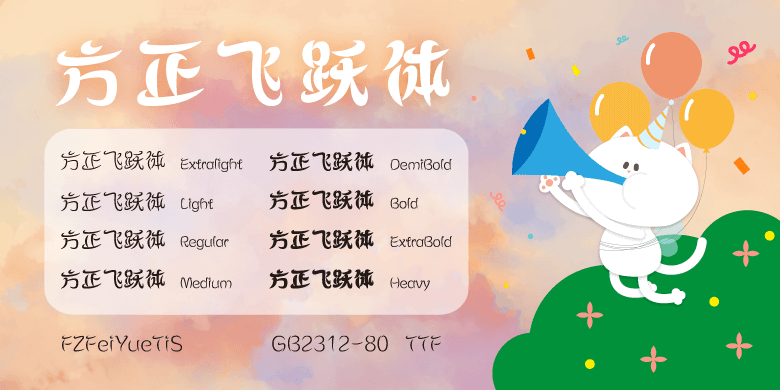
方正飞跃体-简繁-ExtraLight
方正飞跃体:一看这名字感受到活力和跳跃的感觉,设计灵感来源于郭老师在看运动会跨栏赛跑时,发现该名运动员的跑鞋上的标志,立即抓了这条大鱼(灵感)。飞跃体的特点是没有直线,全是弧线组成,横划都向右上角斜上,头部有一个弯钩,所有撇,捺,点都用弧线形表达,因此增强飞跃体的感觉,名副其实,飞跃体在设计上突破传统束缚,并带来创新悦目的感受,它含有8款粗细,适合年青人的品牌,饮料,体育用品和包装等广告宣传!